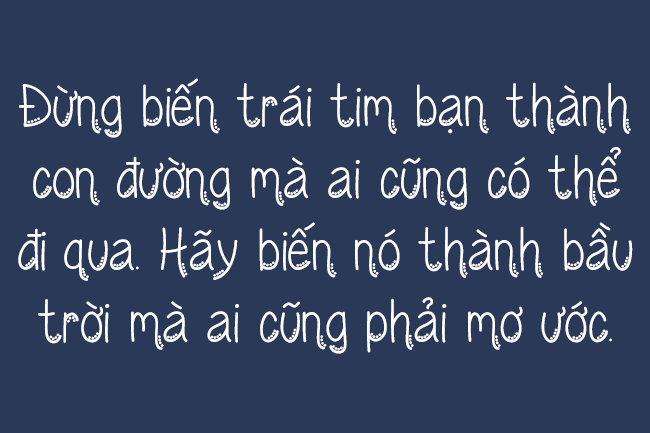
Wednesday là một font chữ trang trí cầu kỳ, được thiết kế bởi Vanessa Bays. Font được cấp phép miễn phí cho mục đích sử dụng cá nhân. Bạn có thể tải về và sử dụng font này miễn phí cho các dự án cá nhân. Đối với các dự án thương mại, vui lòng tham khảo tệp giấy phép đi kèm trong gói font hoặc liên hệ trực tiếp với nhà thiết kế tại bythebutterfly.com.
Nhà thiết kế: Vanessa Bays
Nhà phát hành: ByTheButterfly.com